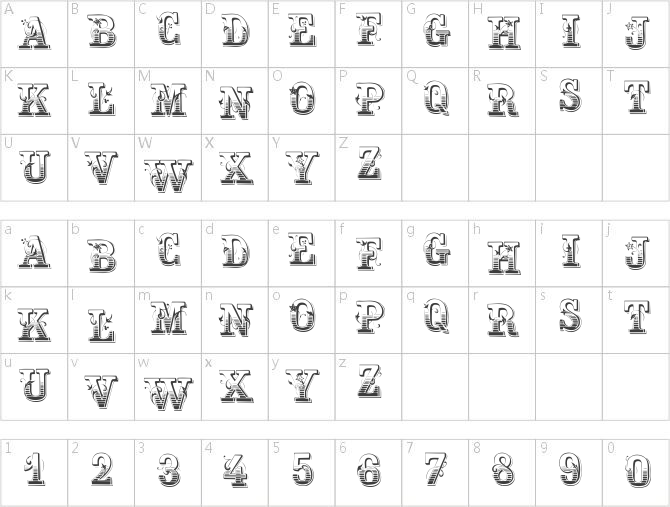
Holtzschue Regular 詳情頁
Holtzschue Regular字體字庫(kù)是一款讓人賞心悅目、百看不厭的英文字體,適合各類廣告和產(chǎn)品包裝設(shè)計(jì)應(yīng)用,字體大小0.08MB,格式為ttf字體,上傳用戶是青檸檬,作者/版權(quán)方為未知